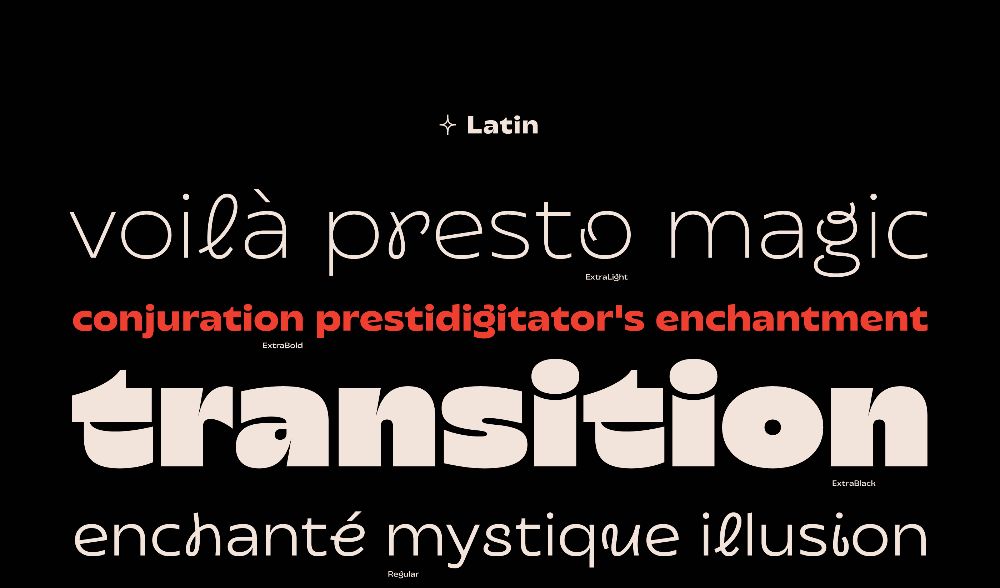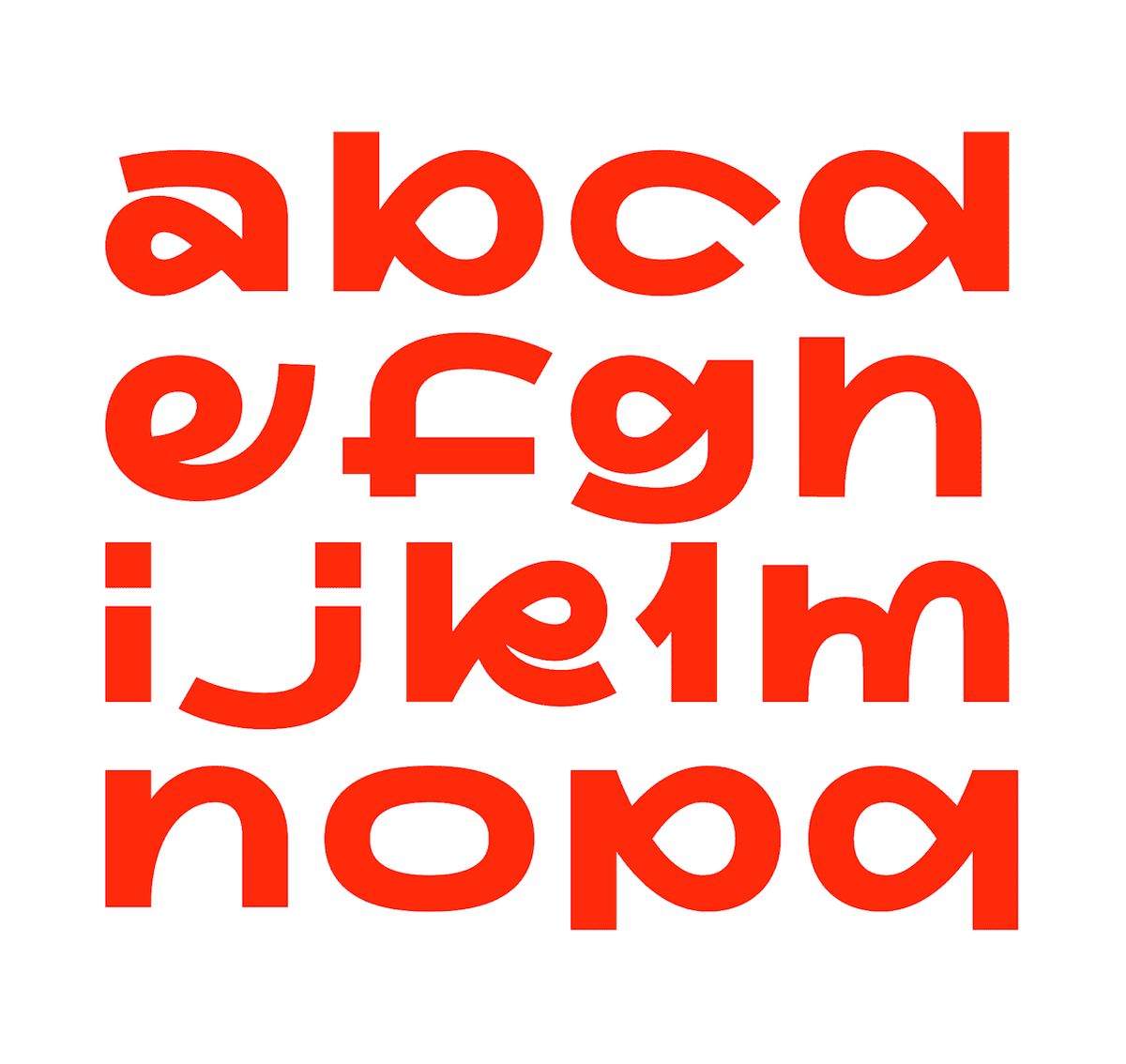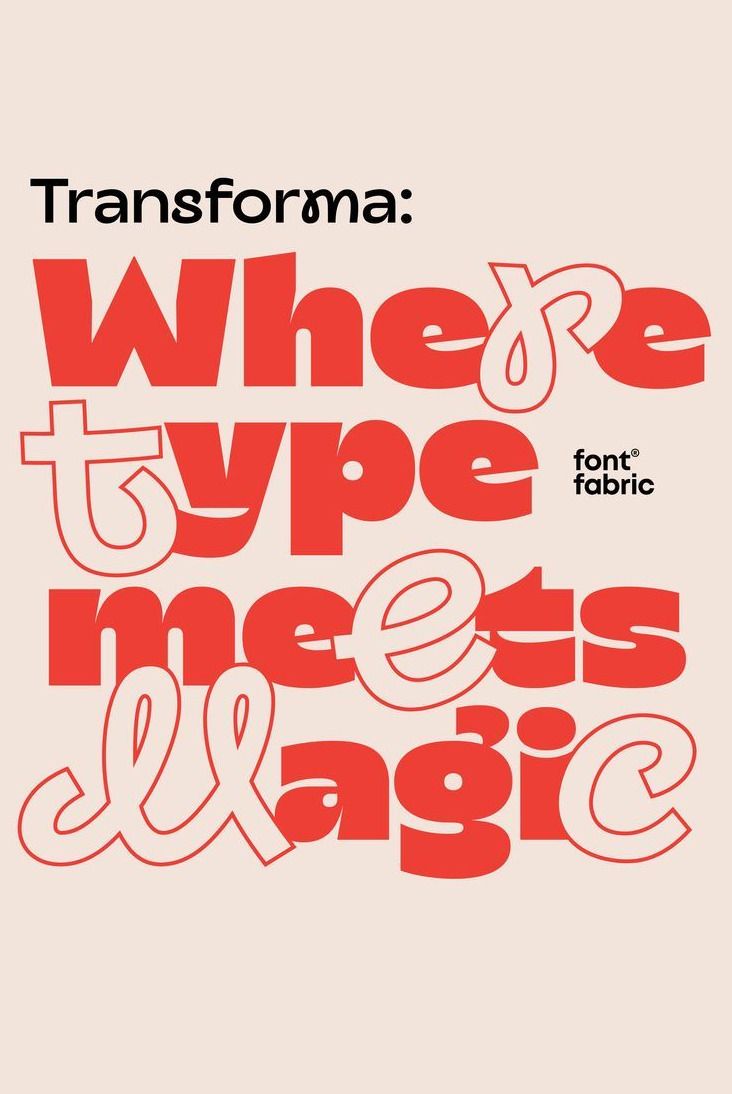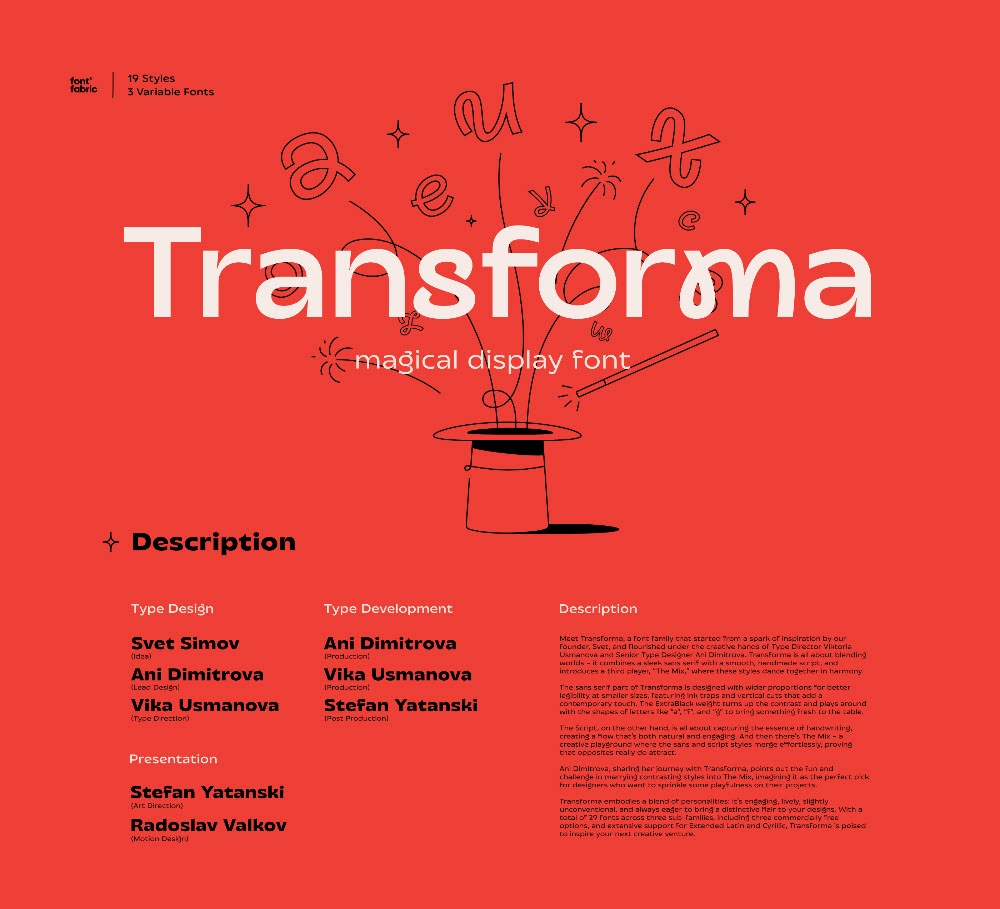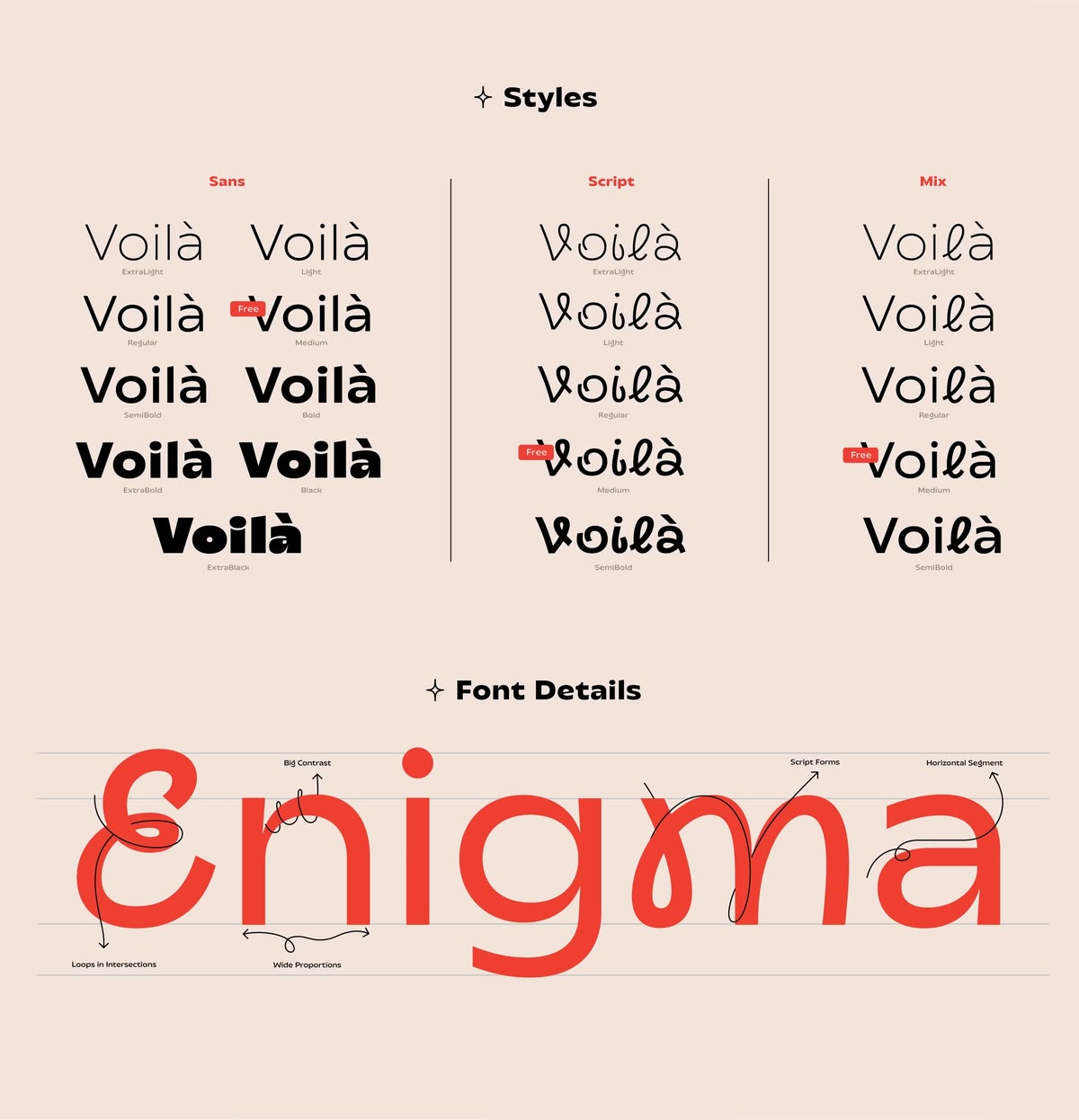
Transforma font family là gì?
Transforma là một “siêu gia đình” phông chữ (Super Family) vô cùng linh hoạt, bao gồm cả hai biến thể Mix và Script. Điểm độc đáo của Transforma là khả năng biến hóa phong cách từ nghiêm túc, hiện đại đến bay bổng, nghệ thuật chỉ trong một bộ font. Điều này cho phép designer đồng bộ bộ nhận diện thương hiệu từ logo, tiêu đề cho đến các đoạn văn bản dài mà không cần kết hợp quá nhiều phông chữ khác nhau.
Với hơn 20 biến thể khác nhau từ nét cực thanh (Thin) đến nét cực đậm (Black), Transforma đáp ứng mọi nhu cầu từ thiết kế ứng dụng di động đến in ấn bao bì khổ lớn. Bản transforma font family việt hóa mà In Viva chia sẻ đã được căn chỉnh kerning tiếng Việt chuẩn xác, giúp các đoạn văn bản trở nên chuyên nghiệp và thẩm mỹ hơn trên các ấn phẩm cho doanh nghiệp.